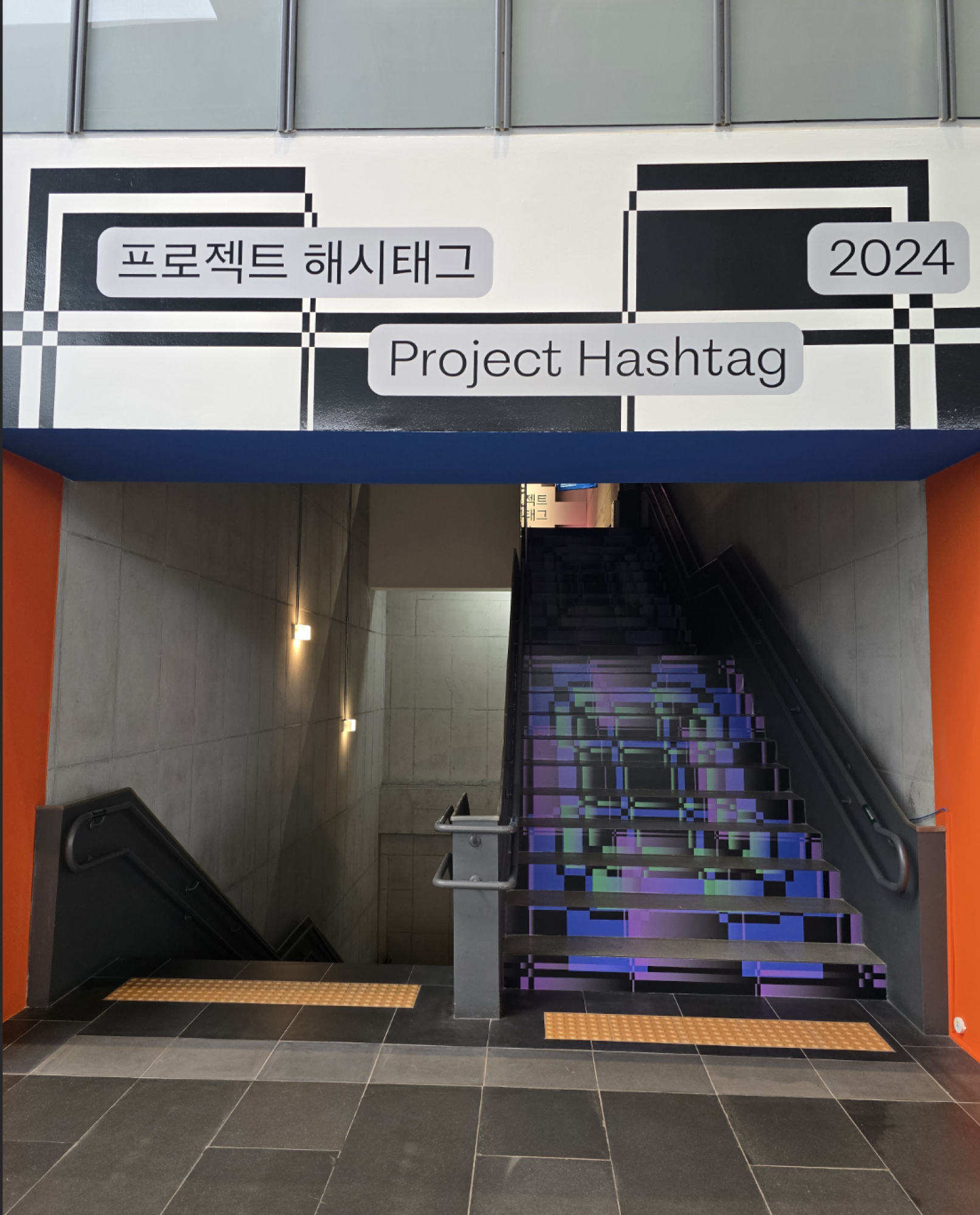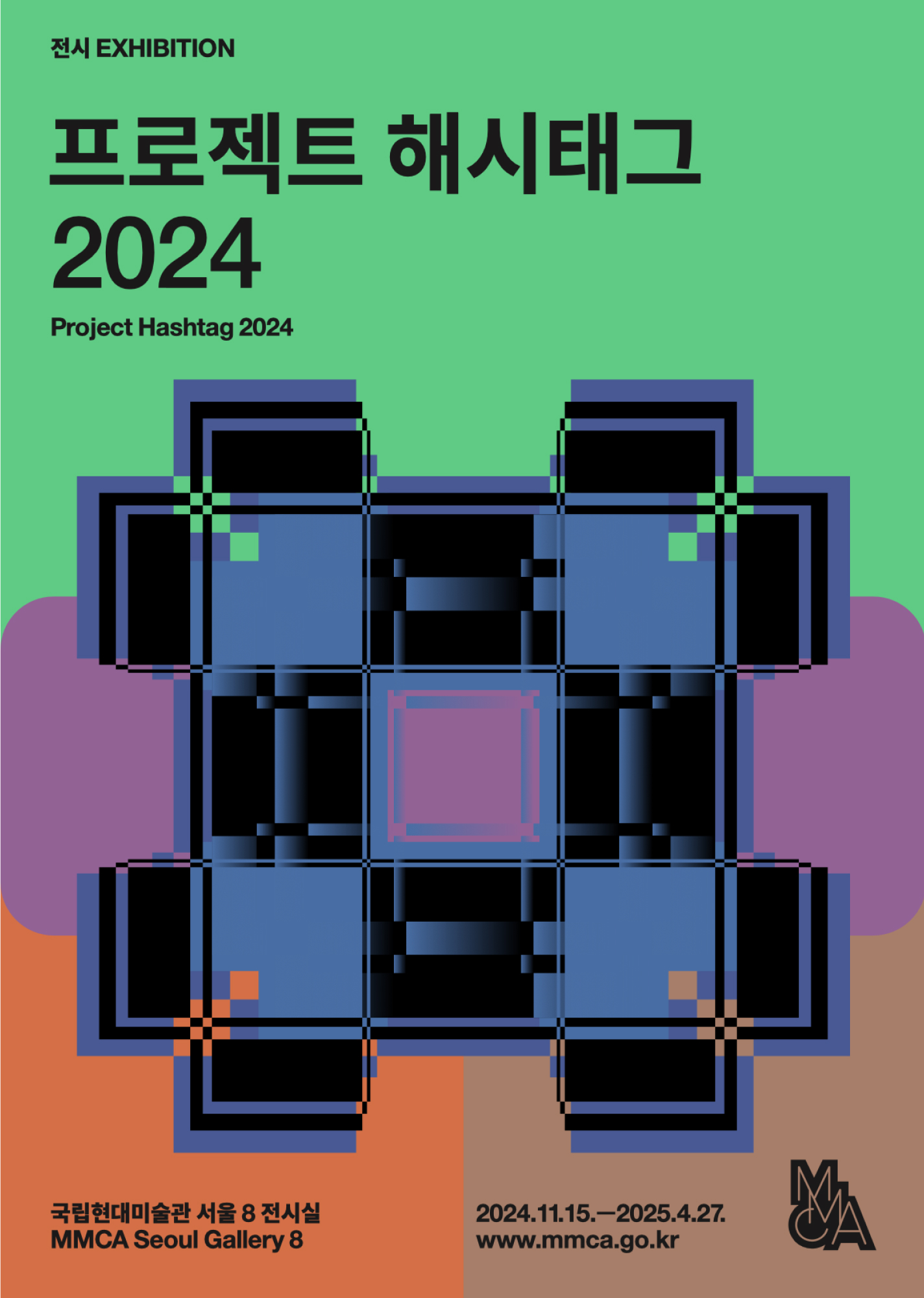
크로닉 그로테스크 Package L
Kronik Grotesk Package L
크로닉 그로테스크(Kronik Grotesk)는 크로닉 시리즈(Kronik Series) 중 하나로 크로닉 안티크(Kronik Antik), 크로닉 비전(Kronik Vision)이 지닌 구조, 형태 및 리듬을 따라갑니다. 크로닉 그로테스크는 전통적인 기하학적 산세리프 비율과 네오 그로테스크 사이의 경계를 넘나듭니다. a, t, f, y와 같은 소문자의 터미널을 더 얇게 유지합니다. n, m, h와 같은 글자의 연결 획은 매우 낮게 시작하여 문단에 역동적인 리듬과 유쾌한 느낌을 불어넣습니다. 이 서체는 큰 제목과 작은 본문 모두에 적합합니다. 현재는 로만 업라이트 스타일만 있지만, 보다 다양한 타이포그래피 레이아웃을 위해 이탤릭 또는 스크립트 버전으로 확장할 계획입니다. 크로닉 그로테스크를 사용해 멋진 레이아웃을 구성해보세요.